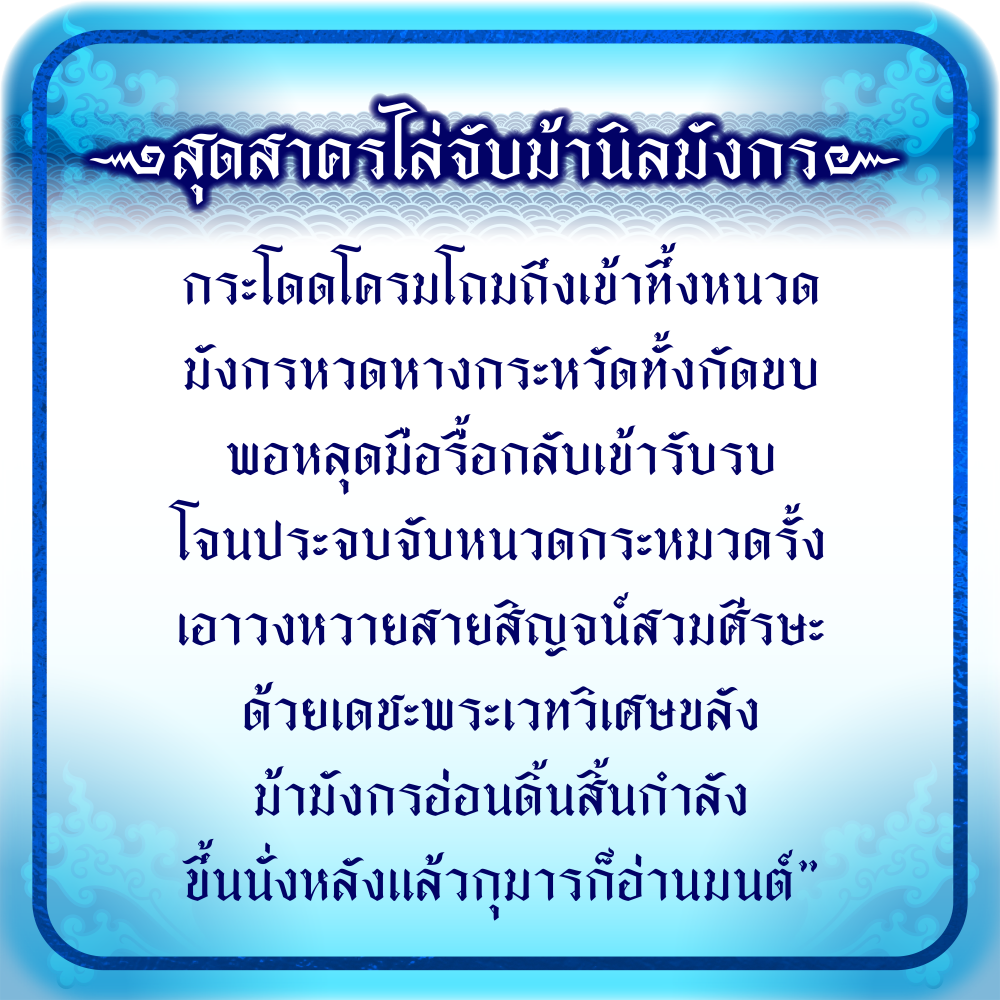
สุดสาคร
ผลงานฟอนต์ที่ชุด 8
ชื่อฟอนต์ สุดสาคร  ลักษณะฟอนต์ไทย เล่นหาง พาดหัว หรือ เนื้อหาบทความได้ นิยาย โบราณ
ชุดตัวอย่างอักษรไทย-อังกฤษ
ลูกเล่นในฟอนต์สุดสาคร ๛
รายละเอียด สุดสาคร
การใช้ kerning ในการจัดช่องไฟระหว่างตัวอักษรทั้งไทย-อังกฤษ
การใช้ mark เข้ามาจัดสระ วรรณยุกต์  เพิ่มการไล่ระดับสระ+วรรณยุกต์ อัตโนมัติ
สระ โ ใ ไ เมื่อเจอกับ วรรณยุกต์ชั้น 2 ไม่มีทับสระและวรรณยุกต์ เช่น กี่ ที่ นี่ นี้ สี่ ตี๋ ปี่ ซี้ กี๊
เจอวรรณยุกต์ชั้นบน เช่น ที่ไป ชี้ให้ ตี๋ให้ จะไม่เจอปัญหาทับกับ โ ใ ไ
อักษรไทยมีลูกเล่นสามารถหางปรับหางยาวได้  ช ซ ศ ส ฮ
ด้วยการกดเครื่องหมาย ++ ตามหลัง ช ซ ศ ส ฮ
สระอุ เปลี่ยนรูปเป็นหางยาวได้ด้วยกดการ " สระอุ ฯ "
เพิ่มวิธีการพิมพ์ โคมูตร ( ๛ ) กด  ฯ147963 ต้องการโคมูตรตัวพิเศษกลับด้าน 147963ฯ
เพิ่มวิธีการพิมพ์ตัวบาลี ญ ฐ แบบไม่มีเชิง ด้วยการกด ญฯฯ  /  ฐฯฯ  จะได้ตัวที่ไม่มีเชิง
ชุดตัวอักษรอังกฤษ เปลี่ยนขาหลบอัตโนมัติ